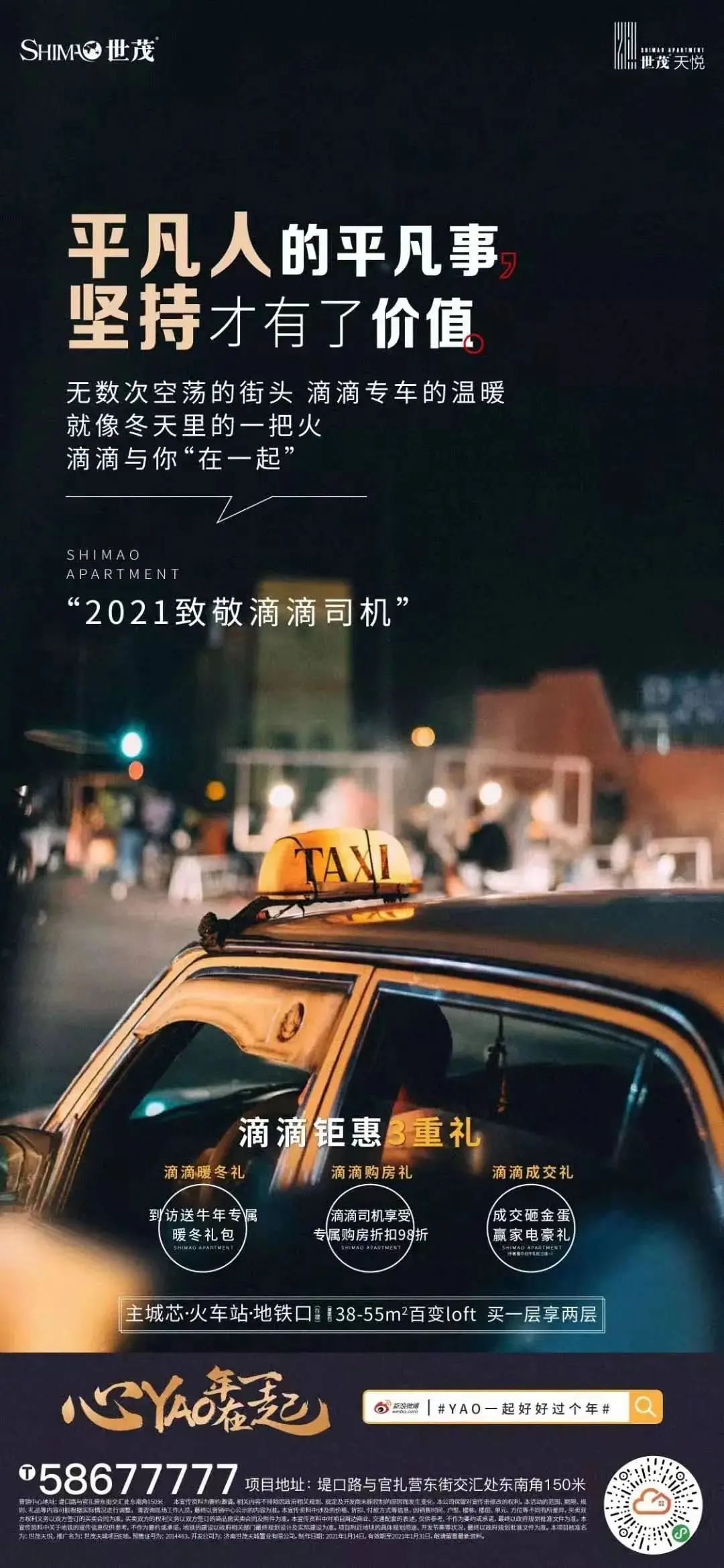
方正铁筋隶书
朱志伟
隶书
2003
方正铁筋隶书采用了隶书的字形结构,但弱化了隶书“蚕头燕尾”的笔形特征。用小篆笔法来书写隶书,用笔均匀细瘦、圆转流畅,笔画存筋藏锋略呈弧度,犹如弯弓蓄势,虽纤细如线却刚劲如铁。这款字体总体给人以宽博舒展、匀净流畅的印象,风格既古朴典雅又富现代气息。适用于各种具有历史和传统文化的语境,如博物馆的展览视觉和宣传品设计。